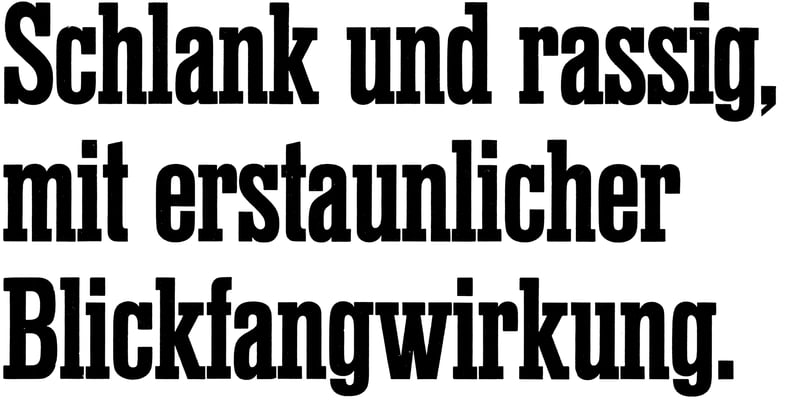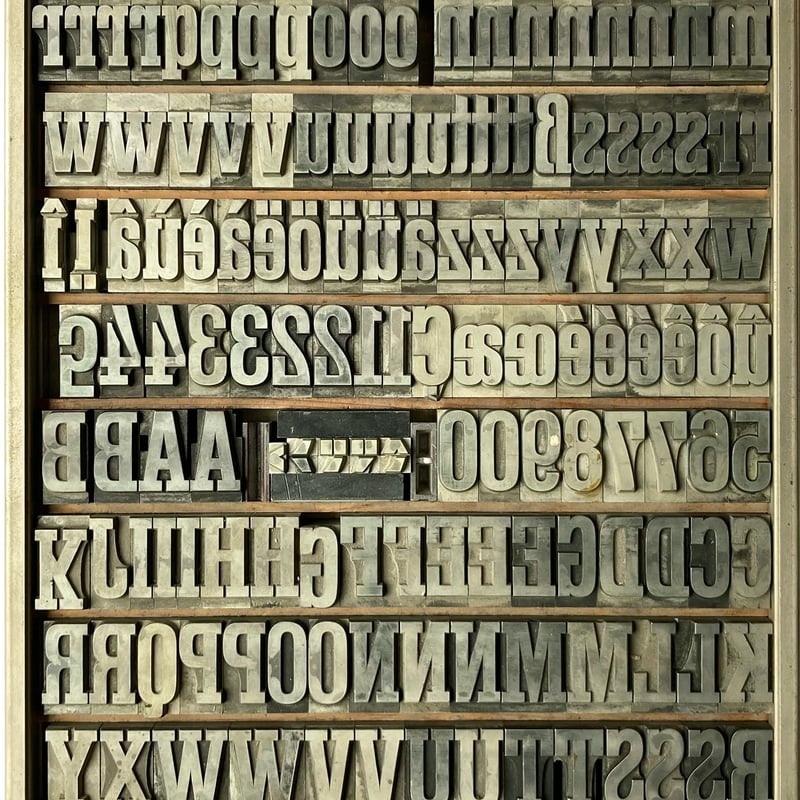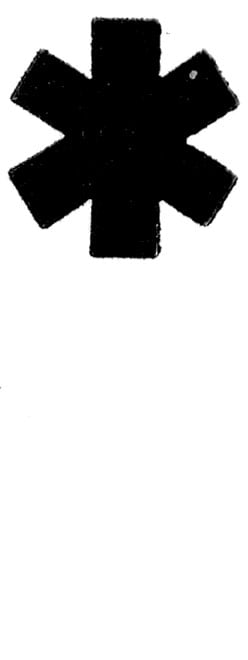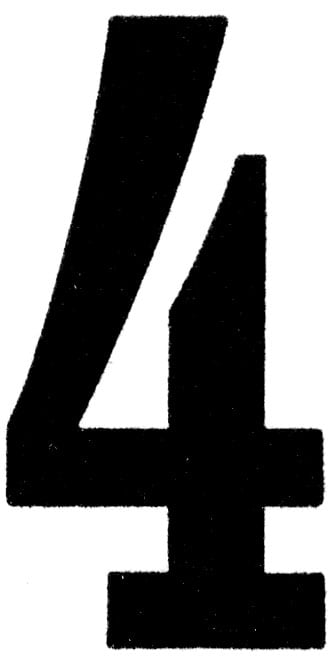
Superba Regular Condensed
Druckmuster mit Text «Superba Schmal, 84pt»
Klassifizierung
Slab Serif
Schriftschnitt
Regular, Condensed
Design
Edmund Thiele
Jahr
1934
Schriftgiesserei
Haas
Die Superba erschien 1934 in zwei Schnitten: Schmal (Condensed) und Licht (auch Superba Illustra). 1937 kam ein fetter Schnitt hinzu. 1940 entwarf Edmund Thiele für Haas die Commercial Grotesk, im Wesentlichen in dem er die Serifen der schmalen Superba abschnitt.